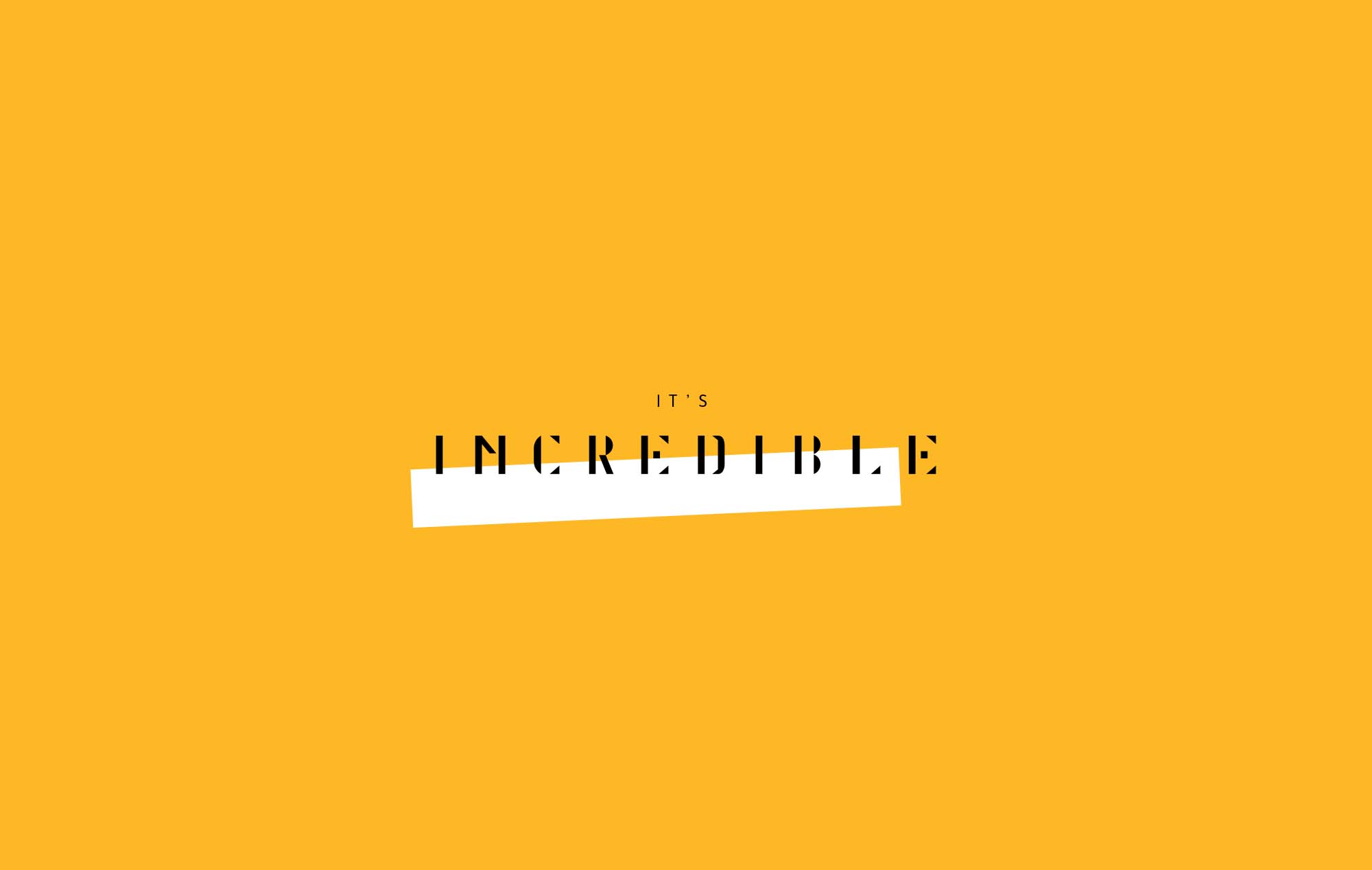
Alaska是一种免费的程式化抽象字体,用于个人和商业用途。它由大写字母以及数字和字形组成。这种字体可用于徽标设计,包装,海报,印刷和网络项目。您还可以将其集成到应用程序开发中,以创建现代高科技设计。此外,您可以使用字母来创建不同的样式和字体的各种变体。阿拉斯加更多的是标题而不是正文。与其他衬线和无衬线字体(如Arial和Helvetica)配对可以产生惊人的效果。